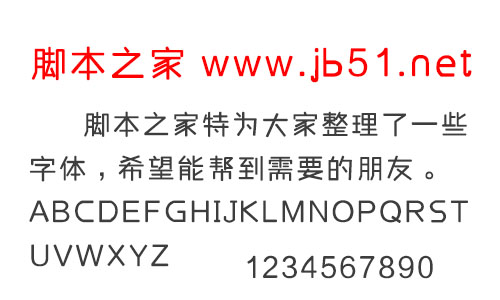
幾何圓體粗字體是在幾何圓體的基礎(chǔ)上加粗優(yōu)化而來,文字更看顯深沉莊重,容易給讀者留下深刻影響,形象鮮明而立體,藝術(shù)效果極佳,幾何圓體粗簡化了漢字中的橫豎撇捺勾踢,讓筆畫點(diǎn)構(gòu)成線,結(jié)合數(shù)學(xué)與語文的特點(diǎn),更加清新,易于閱讀。歡迎喜歡幾何圓體粗字體的朋友前來下載使用。